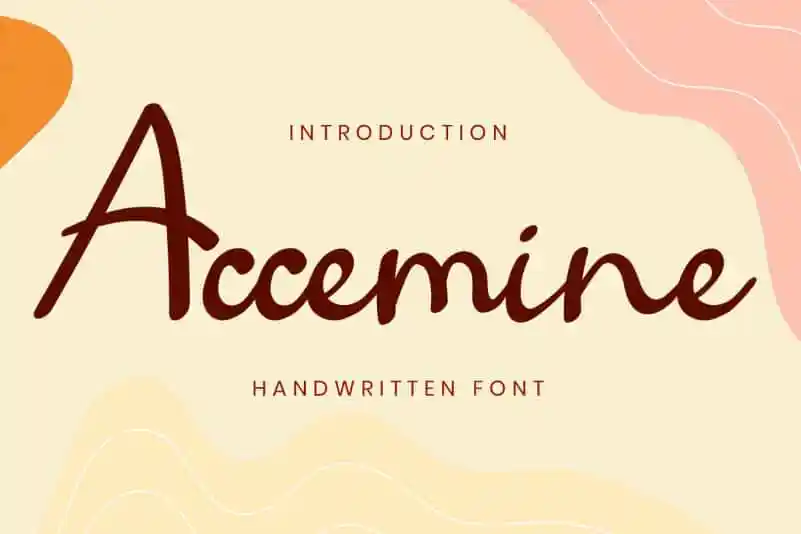
Accemine Script Font – Download Grátis
A Accemine Script é uma fonte escrita à mão com traços suaves e fluidos que não ficará fora de moda em qualquer aplicação do seu design. Ideal para a sua identidade visual, ela irá brilhar nas maiores celebrações como convites de casamento, cartões de agradecimento ou aniversário. Também é uma escolha perfeita para as etiquetas de suas carteirinhas de endereço e logotipos, tornando o seu projeto único e autêntico em qualquer plataforma digital ou impressa. Foi criada pelo Planetz Studio, que produziu esta fonte com uma paixão única por criar gráficos que transmitam sua mensagem de forma mais personalizada e encantadora. A Accemine Script é a escolha perfeita para quem busca um toque único em seus projetos de design.
Designer: planetz studio